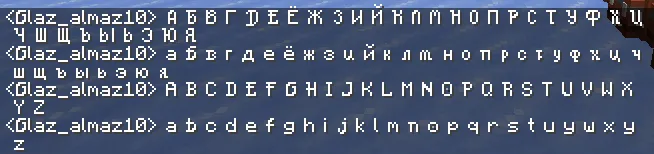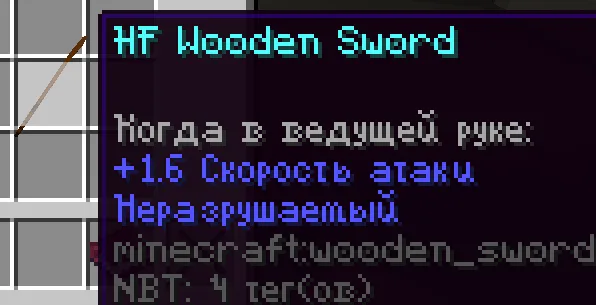
Medieval Font
Этот ресурспак изменяет шрифт в игре на средневековый, похожий на шрифт из игры 'Devil May Cry 5'.
Ресурспак Medieval Font заменяет стандартный шрифт Minecraft на стилизованный средневековый шрифт, вдохновлённый игрой 'Devil May Cry 5'. Новый шрифт придаёт игре атмосферу старины и рыцарских приключений.